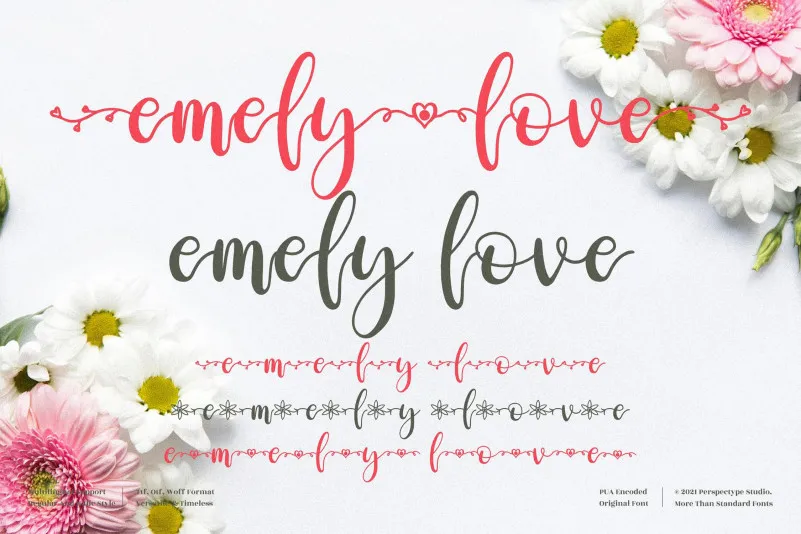
A Emely Love Font é uma elegante fonte escrita a mão com um toque delicado e refinado. Suas letras distintas e equilibradas a tornam verdadeiramente única, fazendo dela uma obra-prima na categoria de fontes script. Seu PUA (Prepend User Area) codificado significa que você pode acessar todos os caracteres e swashes com facilidade, criando um texto impressionante. Este design inovador da perspectype torna o processo de incorporação desta fonte no seu projeto muito simples e prazeroso. Seja para assinatura de livros, materiais educacionais ou qualquer outro tipo de material que deseje dar um toque a mais de elegância e originalidade, Emely Love Font certamente será uma escolha acertada.